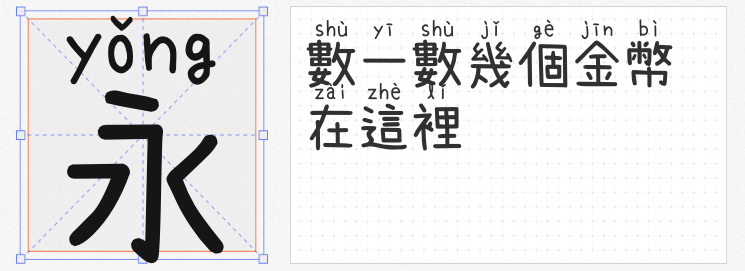
在设计儿童书籍或教育类项目时,带有拼音标注的字体能够极大地帮助学生更快地学习和阅读汉语。今天,就为大家推荐三款专为拼音标注设计的免费商用字体,它们不仅美观大方,而且实用性极强。
1.萌神手写体
这款字体是基于小赖字体改造而成,专为学习中国汉字的学生设计。萌神手写体不仅能够显示日语、简体字和繁体字,还巧妙地加入了拼音标注,使得学生在阅读时能够轻松对应汉字与拼音,加快学习进度。其手写风格也给人一种亲切、温暖的感觉,非常适合用于儿童书籍的排版设计。
2.萌神拼音体
这款字体结合了思源宋体和M+字体的优点,经过精心改造而成。萌神拼音体同样具备拼音标注功能,让学生在阅读过程中能够迅速掌握汉字的发音。此外,它的设计简洁大方,不仅适用于教育类设计,还能在某些商业设计场景中展现出独特的魅力。
这款字体是在原字体视界法棍体的基础上加入了拼音标记,使得其不仅保留了法棍体的独特风格,还具备了拼音标注的功能。字体视界法棍体拼音版的设计现代而富有创意,非常适合用于教育类项目的宣传设计,能够吸引学生的注意力,提升学习效果。